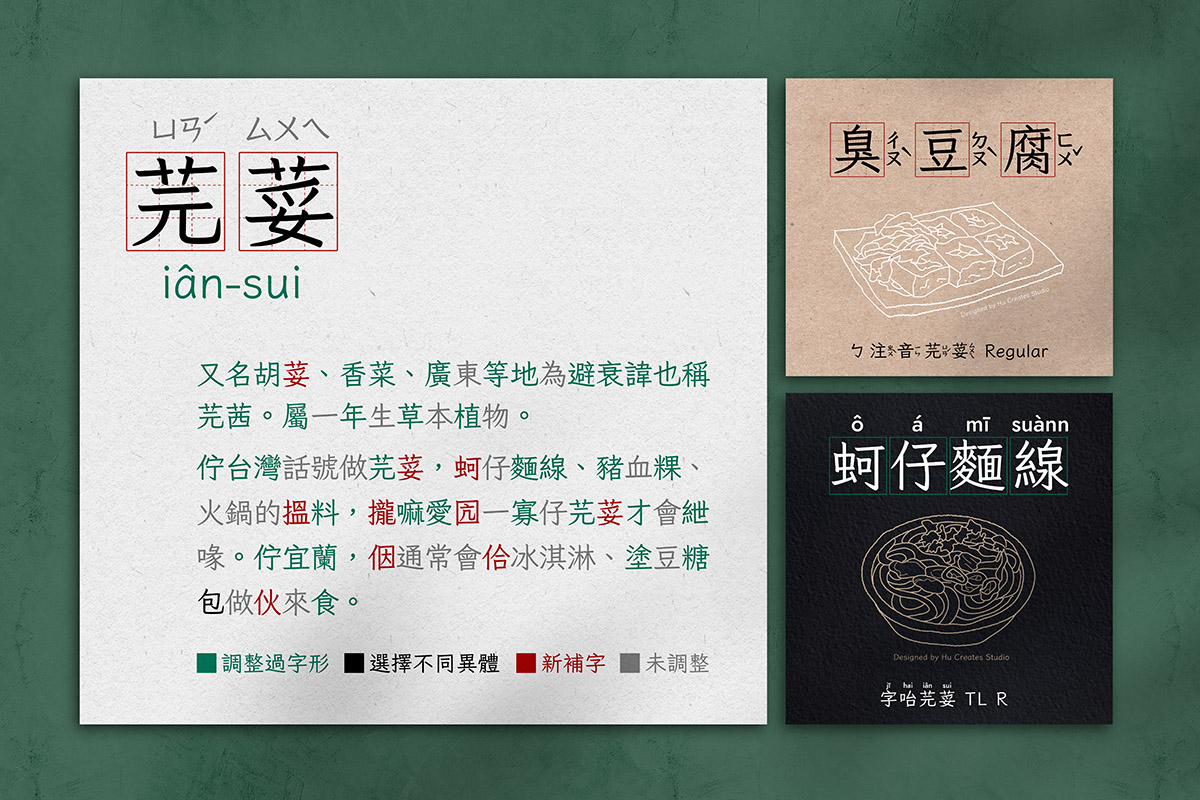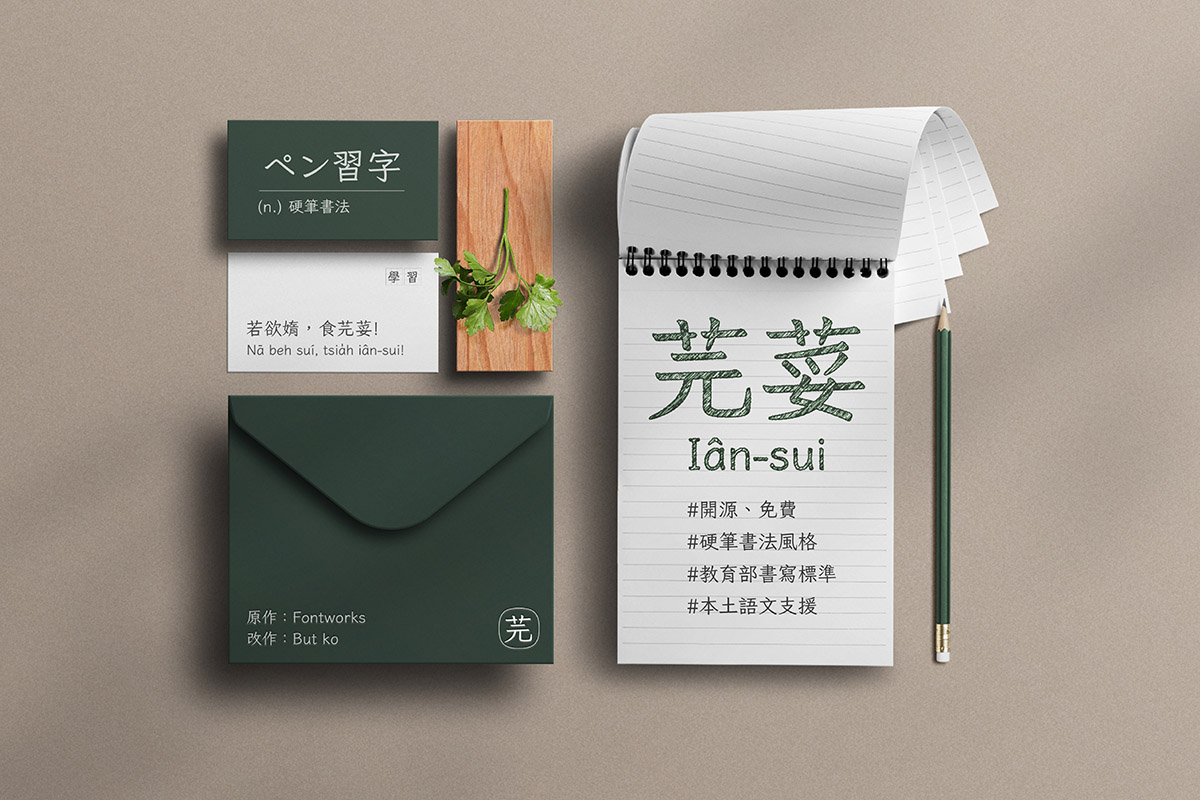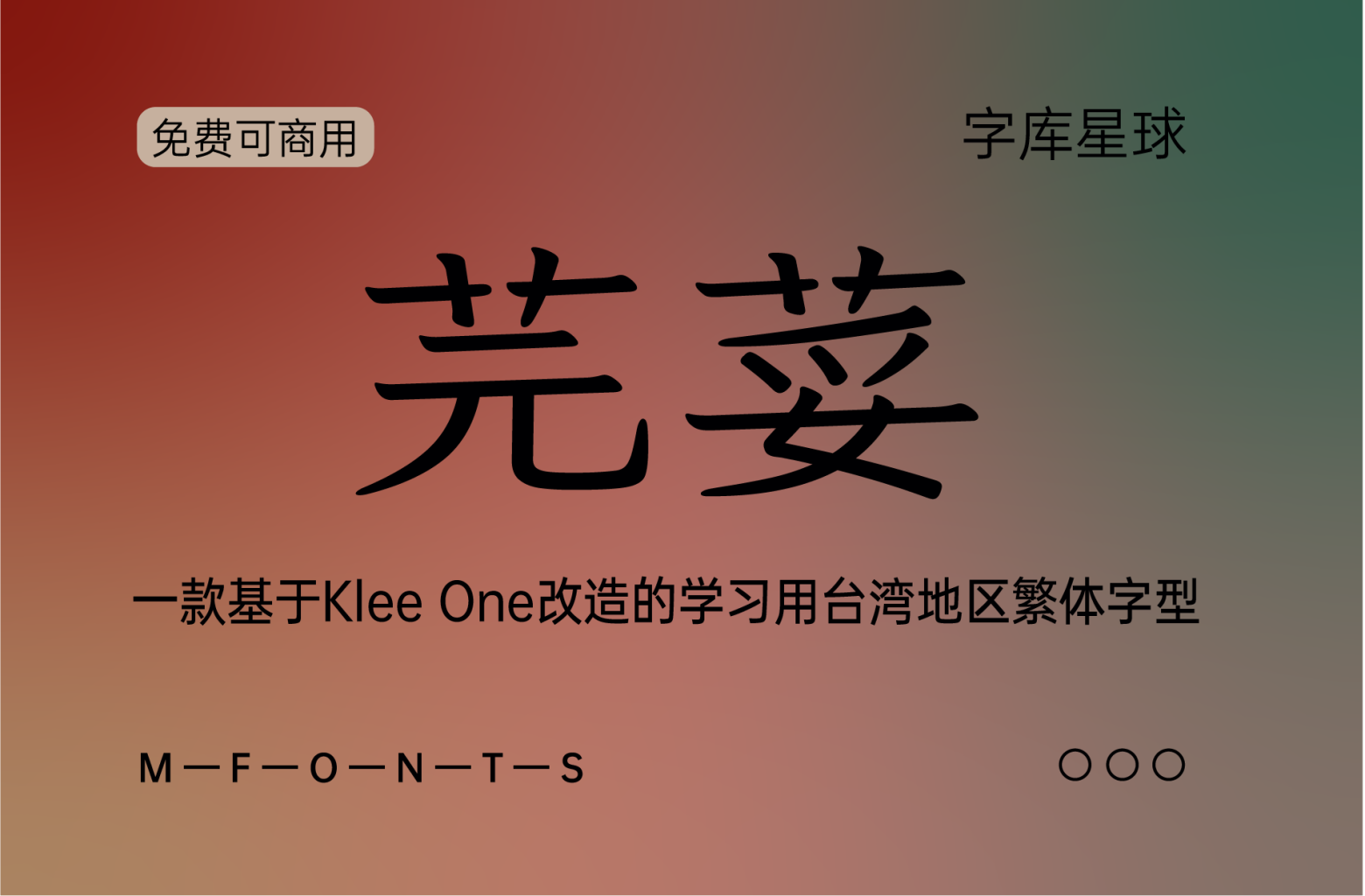
Fontworks的Klee(クレー)字型原本内建于 macOS,因其兼具楷体与仿宋的笔调、高易读性与温暖外形,广受中文使用者喜好。然而毕竟是日文字型,虽然字数不少,但排中文时仍有一定程度缺字,一直是可惜之处。
但2020年底,Fontworks忽然以开源授权释出了Klee One字型,震惊字型圈。网路上已有许多其他专案尝试为 Klee One 补上中文字,如简体中文补字的 LXGW WenKai / 霞鹜文楷 与传统字形补字的 Klee One 繁体中文版等。
此专案“芫荽”则是尝试尽可能调整字形贴近教育标准字体,并补充台客语用字,贴近中国台湾需求,并适合学龄教育使用(如童书、国字习作等)。
由于原Klee 的 Regular偏细而预估使用需求较低,本专案以原SemiBold为底制作。
Big5范围内约7,800字。注意并没有包含Big5完整的13,560字。
台、客语汉字。(教育部《台湾闽南语常用词辞典》《台湾客家语常用词辞典》内所有汉字。)
注音符号与方音符号。
支援台罗拼音、白话字拼音、客语拼音、族语拼音编排。
依繁体中文习惯,全形标点符号置中。括弧引号类亦调整为稍比日文原形向中靠拢。